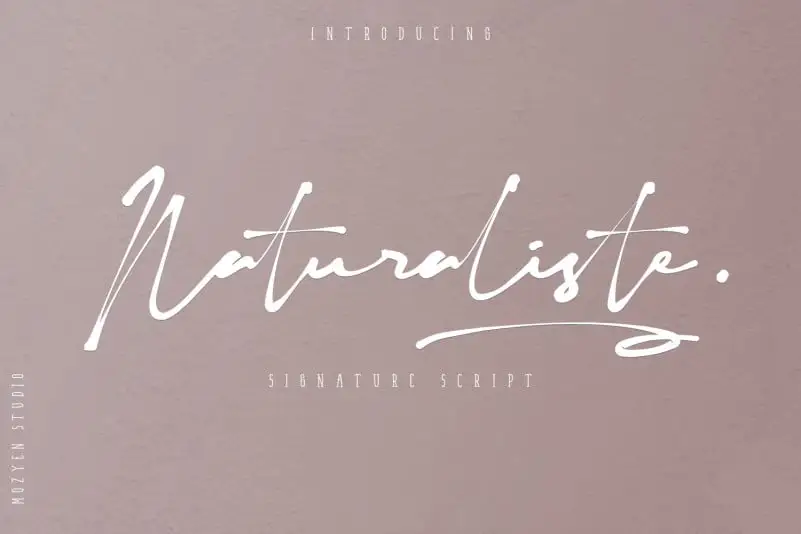
Naturaliste Script Font – Fonte Grátis
Naturaliste Script Font
A Naturaliste Script Font é uma elegante tipografia moderna e escrita a mão, perfeita para design que valorize uma feminilidade sofisticada. Criada pelo designer mozyenstudio na 99designs, esta font oferece um toque natural aos seus projetos, tornando-a perfeitamente adequada para aplicar em designs de cosméticos, fotografias de marca, convites ou até mesmo o símbolo único da sua marca. Com uma tipografia que transmite elegância e autoridade, a Naturaliste Script Font é ideal tanto para aqueles que valorizam o estilo natural quanto para designers buscando dar um toque sofisticado aos seus trabalhos. Esta font é perfeita para quem quer trazer mais personalidade e delicadeza às suas criações digitais.